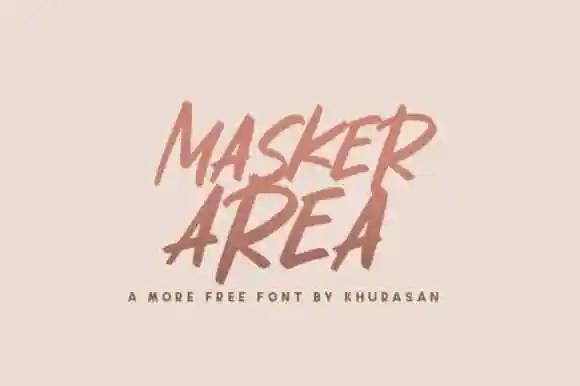
Masker Area Brush Font – Download Grátis
A Masker Area Brush Font é uma fonte script livre criada por Khurasan com traços grossos e caracteres divertidos. Esta elegante fonte é perfeita para criar um visual interessantemente desenfadado, seja em anúncios, logomarcas ou qualquer outro design que exija um look atraente. A Masker Area Brush Font foi projetada para trazer uma sensação de criatividade e versatilidade aos designs. Para usufruir ao máximo da sua leveza e naturalidade, Khurasan adicionou traços rústicos e funções únicas à fonte. Esta combinação resulta em um estilo distintivo que irá tornar seu design único e atraente. Com Masker Area Brush Font, é fácil criar designs impactantes e autênticos que se destacam dos demais. Esta fonte de script está disponível no formato ‘Marker’, o que permite uma aplicação fluida para anúncios, logomarcas ou qualquer outra necessidade de design. A fonte também pode ser usada em branding para criar um visual distintivo e memorável. Essencialmente, a Masker Area Brush Font é uma ferramenta versátil para designers digitais que buscam adicionar um toque personalizado e único aos seus trabalhos. Ela oferece uma maneira criativa de trazer a sua marca à vida através do design visual.